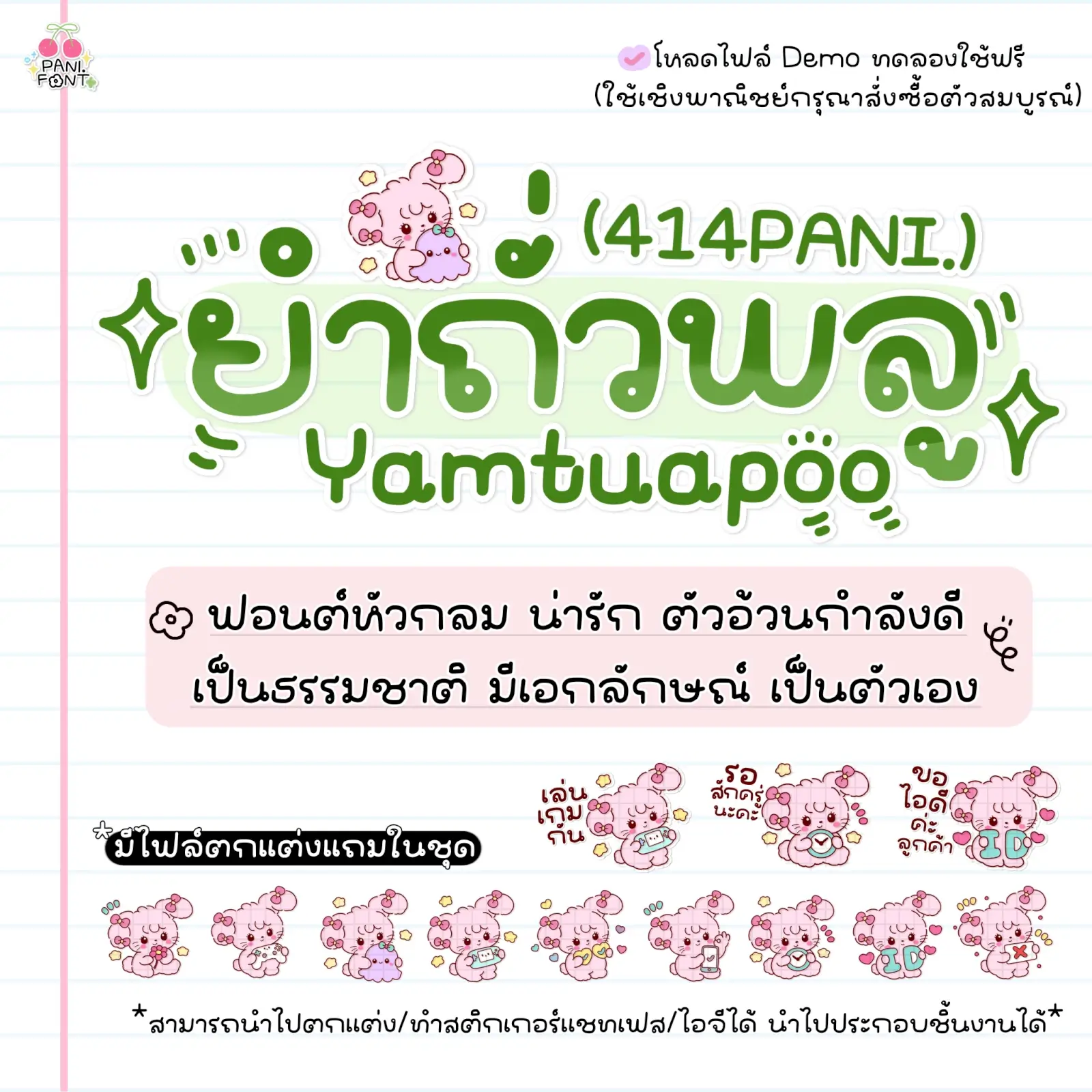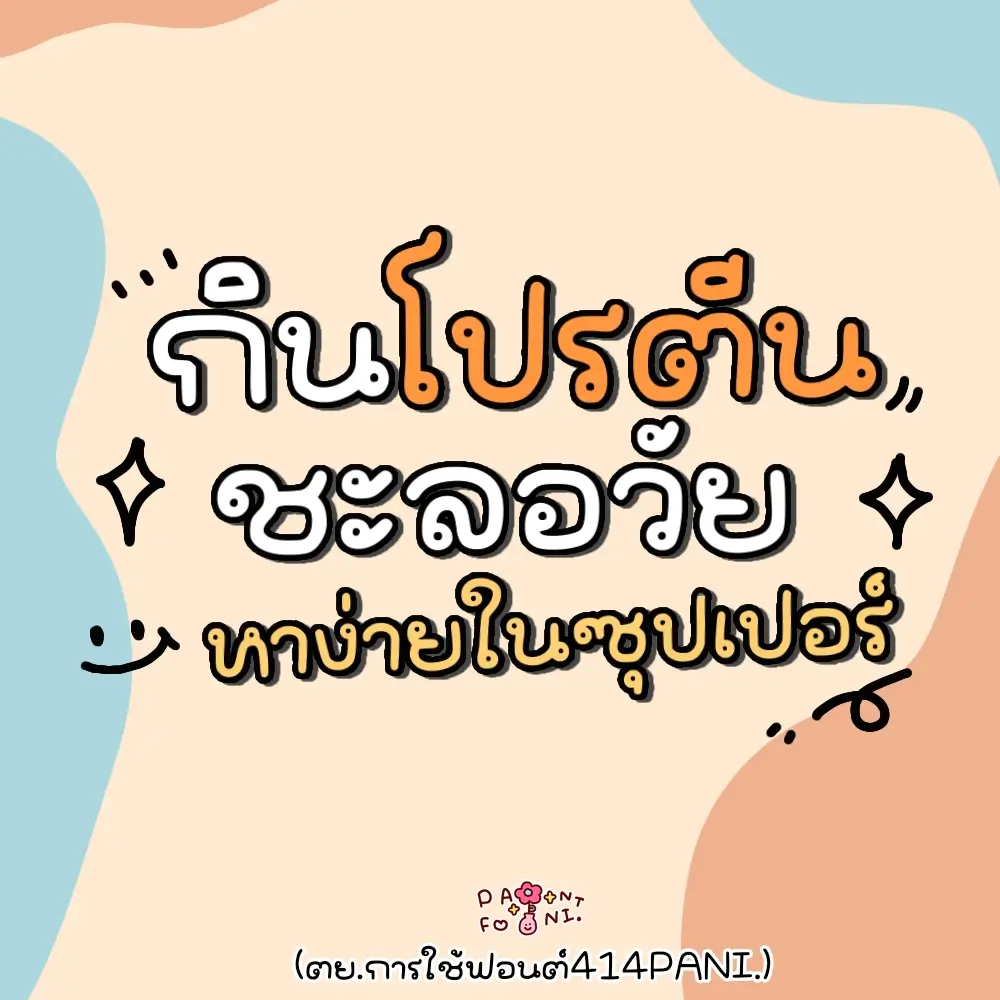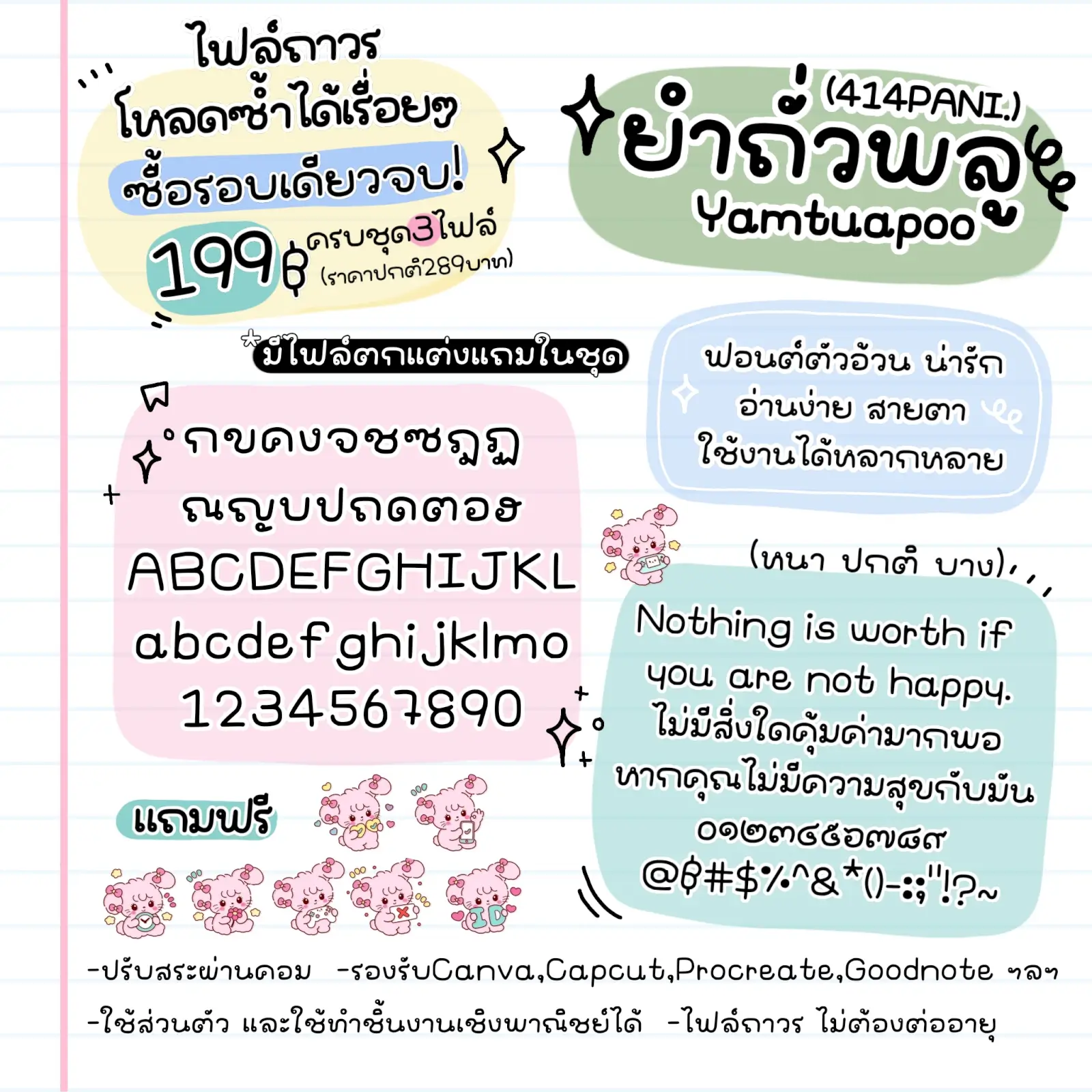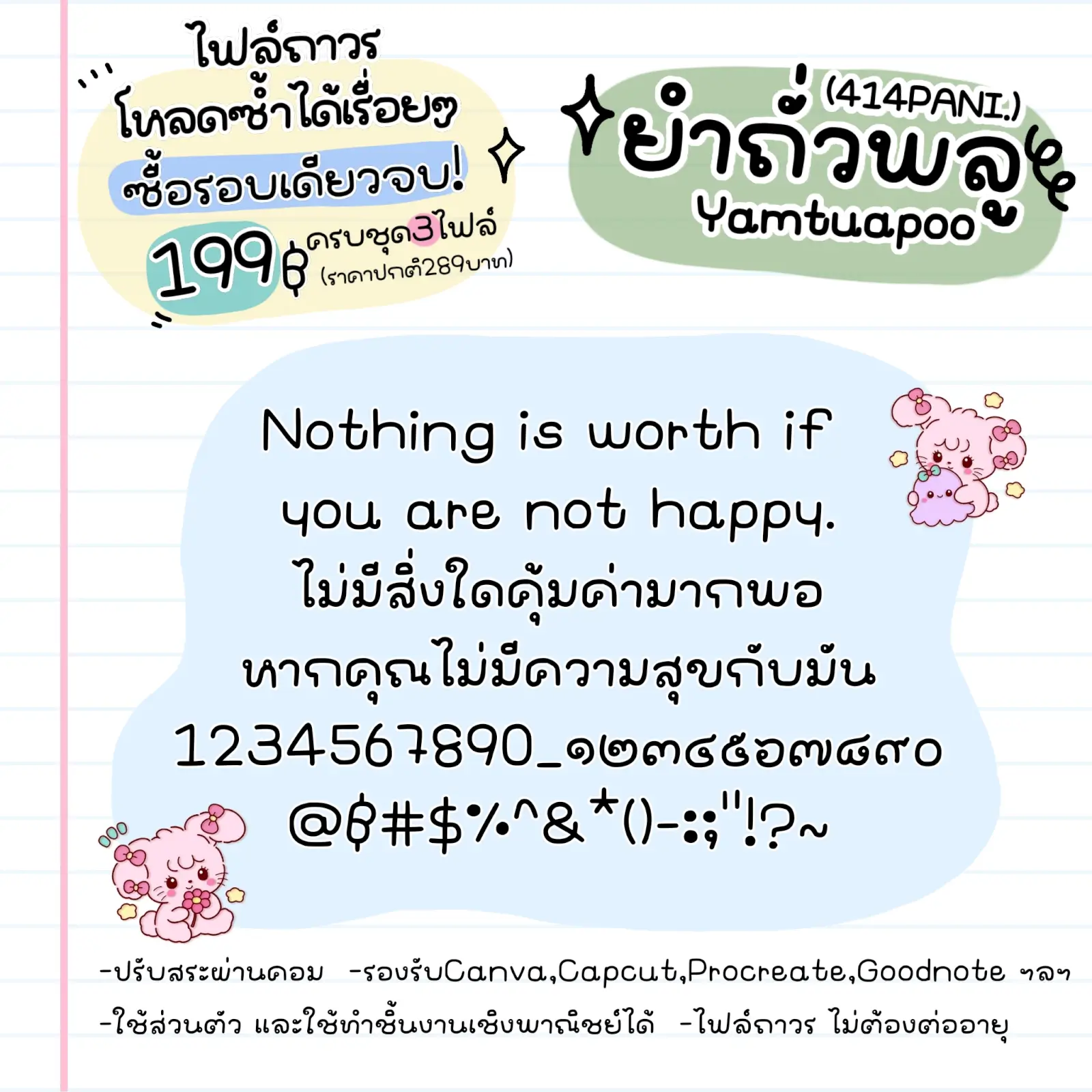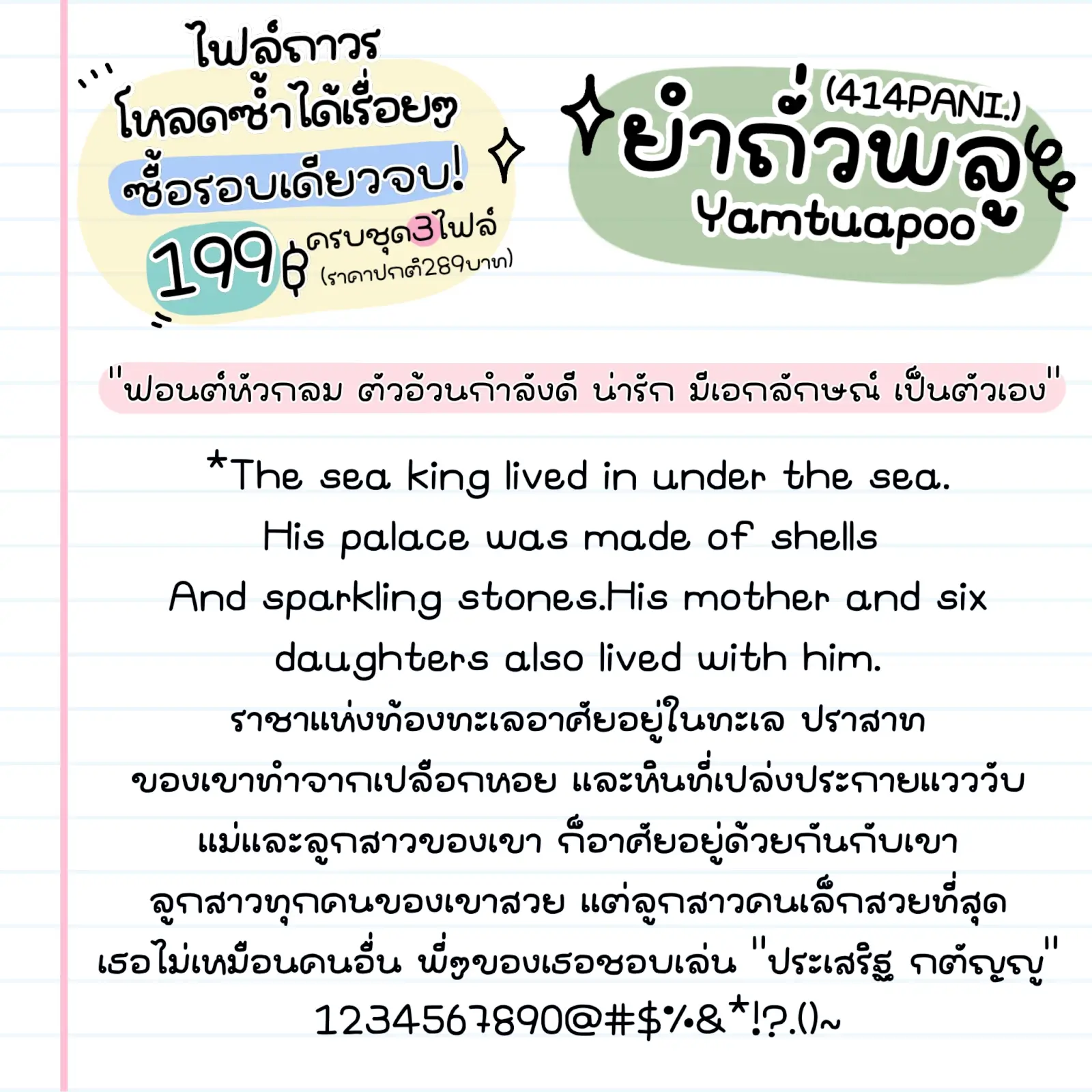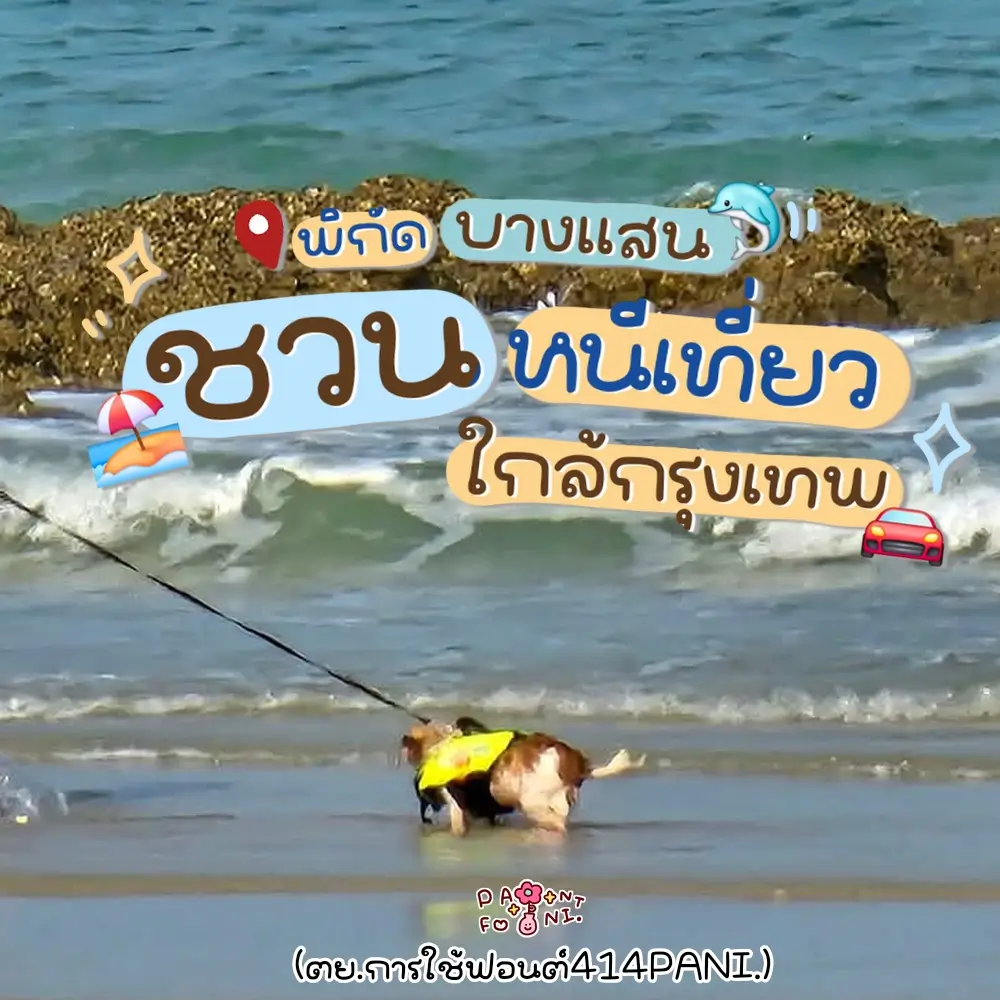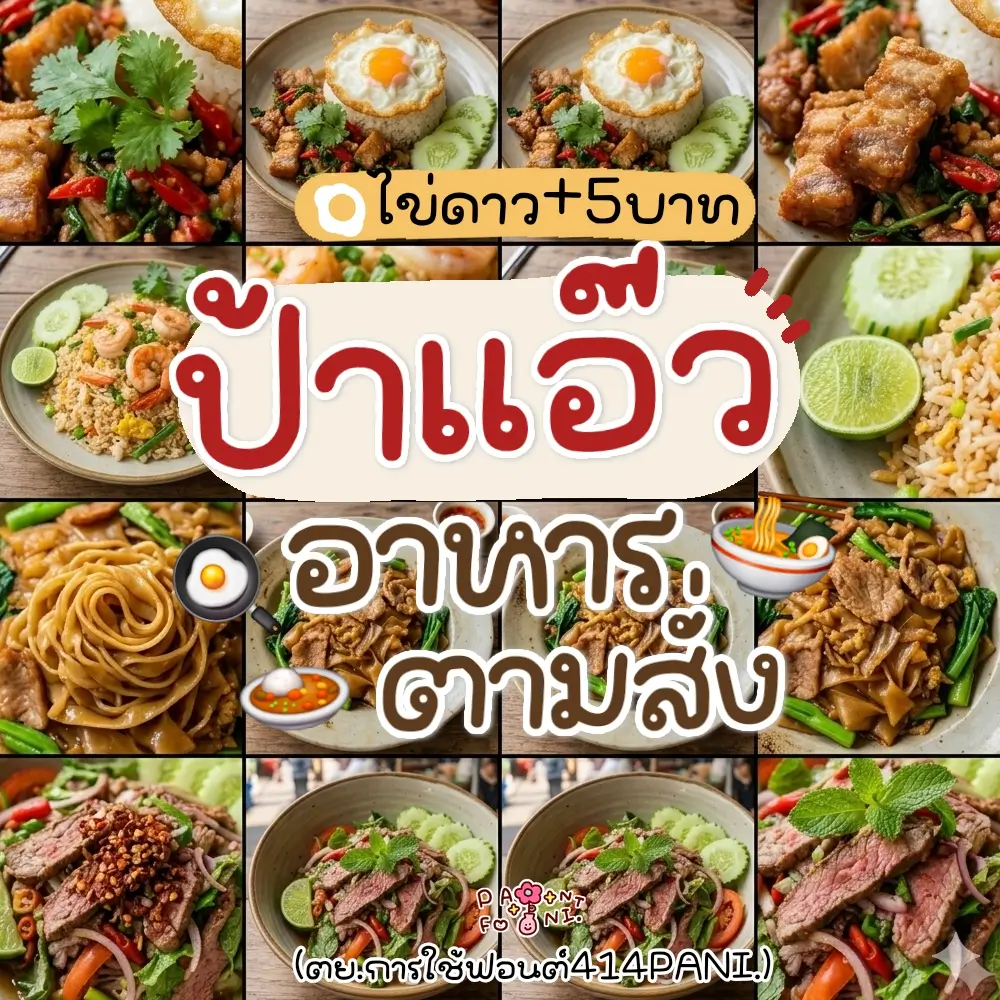
414PANI.ยำถั่วพลู
ฟอนต์ 414PANI.ยำถั่วพลู – ฟอนต์หัวกลม น่ารัก ตัวอ้วนกำลังดี เป็นธรรมชาติ มีเอกลักษณ์ เป็นตัวเอง ชุดนี้แอนทำสติกเกอร์ ของตกแต่งแถมไว้ในชุดด้วยนะคะ สามารถนำไปใช้กันได้ค่ะ